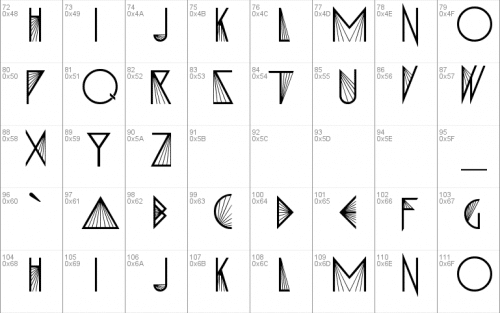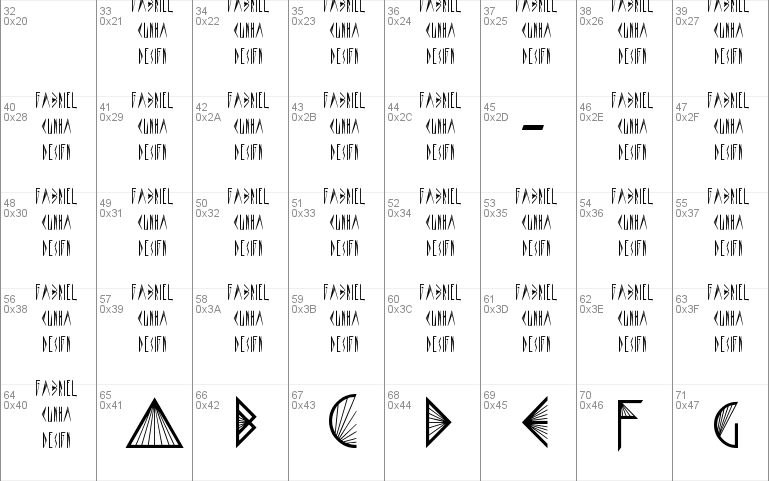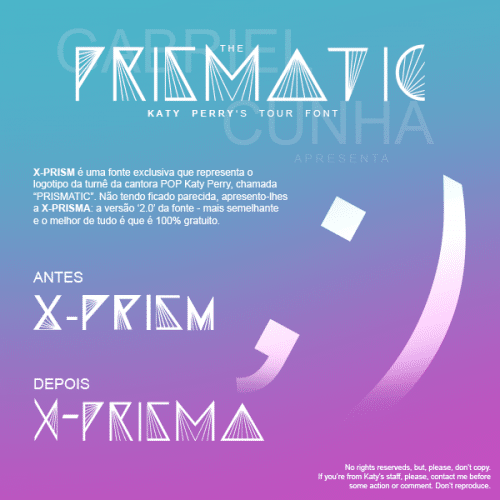
Após a fonte “X-PRISM” (inspirada no logotipo da turnê da cantora Katy Perry, a Prismatic Tour), aqui vai a versão 2.0 da mesma ? a X-PRISMA está pronta para download! Bom uso a todos. (After the font “X-PRISM”, here is the new version ? the X-PRISMA is ready for download! Good use for everybody.) As restantes letras que não compõem o título da tour foram criadas e editadas por mim. (The other words are created by myself.)